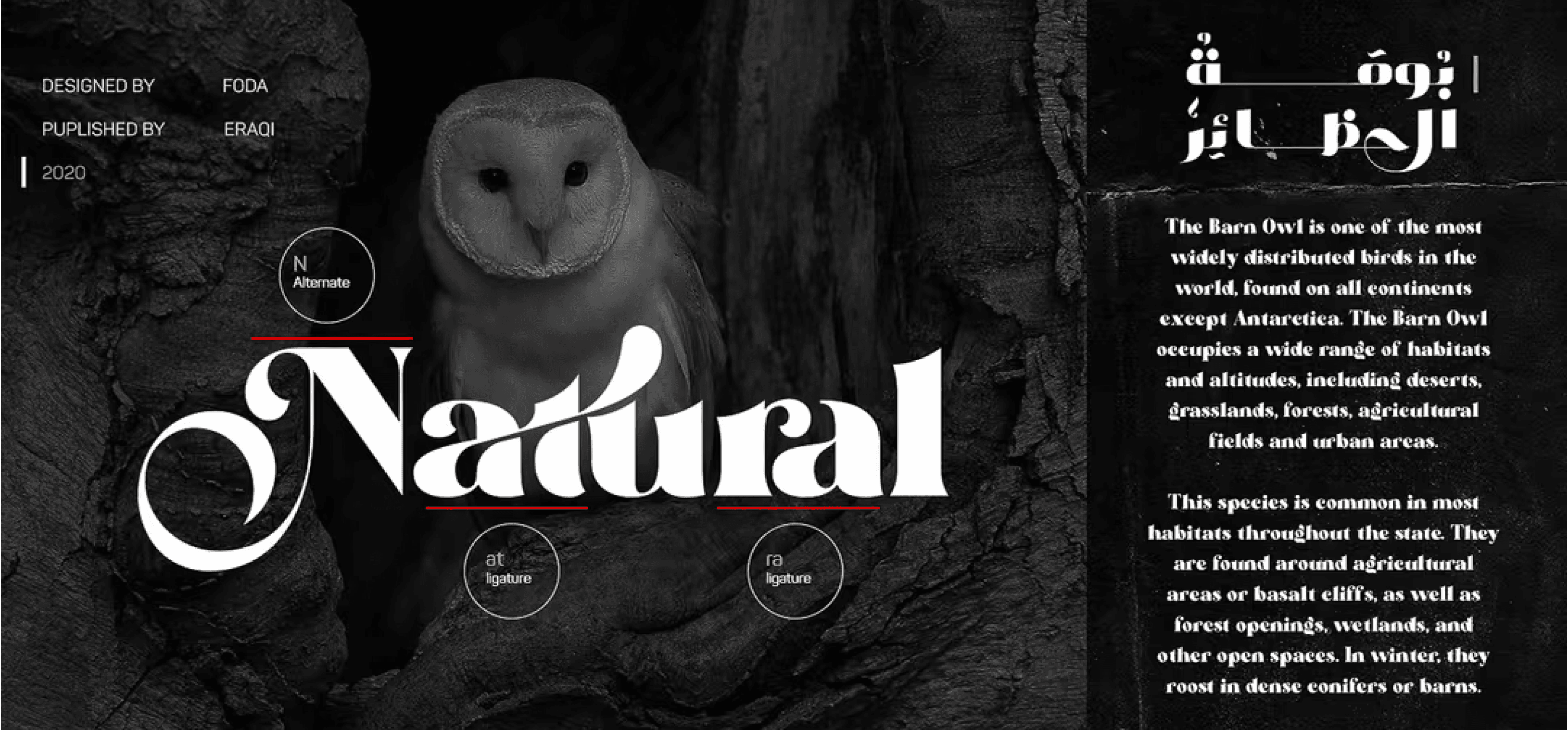
هو خط عرض يتميز بتباين عالٍ ويأتي بوزن واحد فقط.
يدعم العديد من اللغات اللاتينية بالإضافة إلى اللغة العربية، ويحتوي على ما يقارب 900 رمز (Glyph) تغطي العديد من ميزات OpenType، مما يجعله مناسبًا للتصميمات المتنوعة والعناوين اللافتة للنظر.